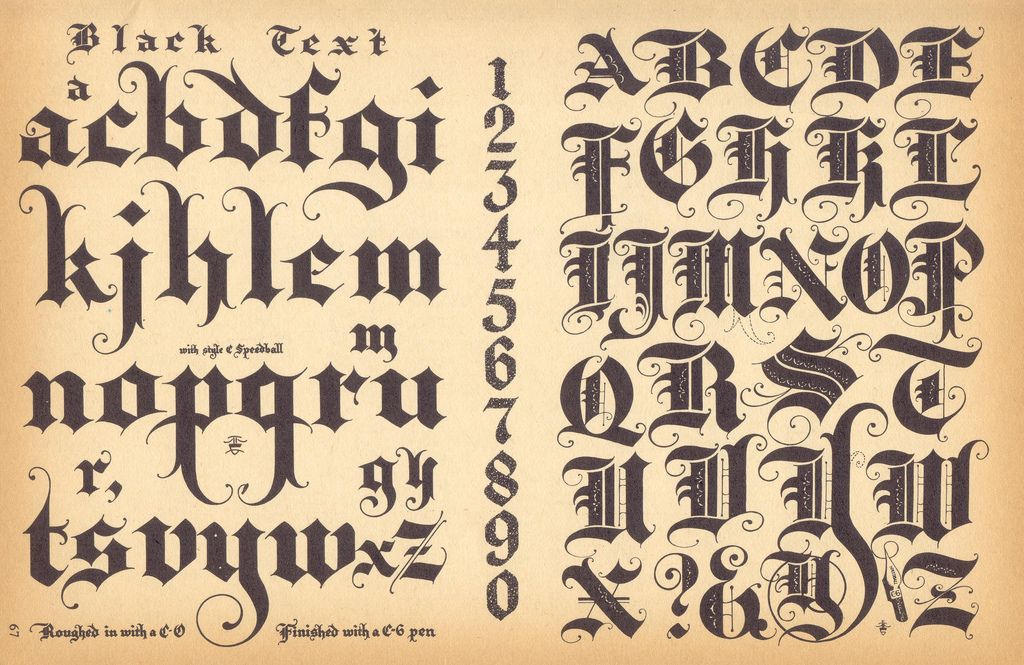
Futura: красота под давлением
Паулю Реннеру удалось создать шрифт, который настолько же технически совершенен, насколько и элегантен.
Сенгай, “Вселенная” — знаменитая каллиграфия японского мастера, написанная тушьюFutura родилась в одно время с целым рядом немецких гротесков в конце 1920-х годов.
Эти шрифты полностью отражали прогрессивный, модернистский дух своего времени. В какой-то момент, преодолев первоначальное сопротивление, Futura была выбрана для обслуживания нацистской пропаганды. Поскольку она продолжала пользоваться большой популярностью у американских типографий, во время войны шрифт был запрещен в США.
Однако боевые действия остались в прошлом, и со временем высокая читаемость шрифта на приборных панелях сделала его популярным среди дизайнеров ВВС США (они даже использовали его для знака NASA, установленного на Луне). На некоторое время, возможно, из-за повального увлечения Helvetica, он впал в немилость. После 1970-х годов Futura вновь возродилась как идеальная опция для брендинга панковских лейблов-аутсайдеров (таких как Nike, Red Bull или Supreme).
С момента своего появления в 1927 году и до внесения различных изменений, обновлений, создания клонов и новых версий шрифта, Futura прожила необычную жизнь, сравнимую с жизнью Баки Барнса, мрачного персонажа комиксов Marvel. Как пишет Эллен Луптон в предисловии к книге Дугласа Томаса «Никогда не используйте Futura» (2017):
«У каждого шрифта есть своя ДНК, свой голос и своя тайная история интриг и злоупотреблений».Табличка NASA, посвященная высадке на Луну. Заглавными буквами шрифта Futura написано: “В этом месте люди с планеты Земля впервые ступили на Луну в июле 1969 года нашей эры. Мы пришли с миром для всего человечества». Она подписана тремя астронавтами, высадившимися на Луне, и президентом Ричардом Никсоном.Американский актер Себастиан Стэн в роли Баки Барнса и Томми Ли
Как и Баки Барнс, Futura пытается подстроиться под обстоятельства, разобраться со своим проблемным прошлым и примириться с бессмертным телом, которое не стареет.
Это действительно шрифт “рок-звезда”.
Грандиозная непрактичность Fraktur
Отрывок из немецкой газеты 19 века, набранный шрифтом Fraktur. Источник.Немецкий язык, пожалуй, уникален тем, что когда-то он сам был синонимом особого типографского стиля. Сегодня готический шрифт ассоциируется с дэт-металом, но в 1920-х годах он составлял идентичность немецкого языка (его называли «Deutsche schrift»). Немецкий готический шрифт — самостоятельная ветвь эволюции европейской письменности.
Хотя все европейские языки имели одну и ту же базовую структуру, немецкие готические шрифты отличались сложными засечками (некоторые даже выглядят как рога и хвосты) от гораздо более аккуратных надписей, высеченных на итальянских памятниках (отсюда и название “римские шрифты”). Дизайнеры англоязычной типографики все чаще стали приходить к выводу, что буквы в римском стиле выглядят более привлекательно, воспринимаются более эффективно и соответствуют духу времени.
Из витиеватых готических шрифтов с крупными засечками самой большой популярностью пользовалось семейство под названием Fraktur.
В тот период слова “немецкий” и “Fraktur” были синонимами. Ультранационалисты по-настоящему гордились тем, что немецкий язык читался и печатался только в этом мгновенно узнаваемом типографском стиле. В конце концов, считалось, что книгопечатание было изобретено в Германии, и так было задумано самим Гутенбергом.
Для модернистов, однако, Fraktur был головной болью. Гутенберг выбрал этот шрифт случайно — он просто имитировал каллиграфический почерк, не задумываясь о том, что печатная технология позволяет создавать новую разборчивую и удобную для чтения типографику.
Fraktur совершенно не вписывался в новую механическую эпоху. Детям в начальной школе было очень трудно учить такие буквы (особенно, если сравнить с простыми рукописными шрифтами, разработанными на основе каролингского минускула). Шрифт был слишком декоративным для основного текста и не мог сравниться по уровню читабельности с римскими аналогами, если речь шла о маленьких размерах или больших блоках текста. А ведь это было просто необходимо для форматов массовой печати, которые распространялись в беспрецедентных масштабах (газеты, дешевые романы в мягкой обложке или инструкции на приборных панелях).
В начале 1920-х годов, как упоминает Кристофер Берк в своей биографии Пауля Реннера, многие политики склонялись к идее о необходимости обновления немецкой типографики. Однако в связи с крайним ужесточением политики к началу 1930-х годов ни один из них не мог осмелиться даже подумать о прогрессивных реформах. Fraktur не должен был подвергаться сомнению. Любая попытка изменить дизайн в соответствии с новыми идеями эпохи немедленно интерпретировалась как оскорбление истории, традиций и величия Германии.
«Где хорошее современное искусство?»
В 1928 году Пауль Шульце-Наумбург, всемирно известный художник, архитектор и законодатель общественных вкусов, опубликовал книгу под названием «Искусство и раса» (Kunst and Rasse). Нацисты вообразили себя поборниками справедливости, призванными защищать немецкую культуру, в том числе Fraktur, и стали относиться к модернистскому дизайну почти с такой же иррациональной яростью, ненавистью и мстительностью, с какой они обычно относились к евреям.